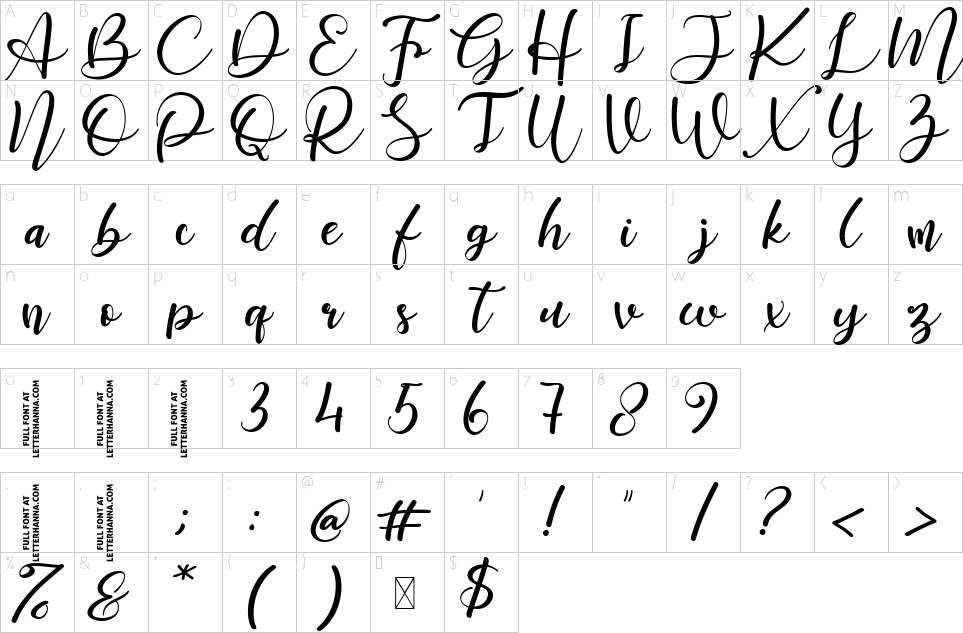
Groovy Soumaya Font
A Groovy Soumaya é uma fonte moderna e divertida que combina elegância com uma pitada de descontração. Ela foi criada pelo designer Rinaldo Hasibuan, trazendo um toque vibrante à escrita. Esta fonte gratuita pode ser usada tanto em versões para Windows quanto para Mac. Com seu design alegre e sua facilidade de leitura, Groovy Soumaya é uma escolha ótima para designers buscando uma fonte que combine modernidade com um toque amigável. Com mais de 1.993 downloads desde sua disponibilização, não há dúvida de que muitos usuários já estão se beneficiando da versatilidade desta fonte única e divertida.
Mapa de caracteres da fonte Groovy Soumaya Font